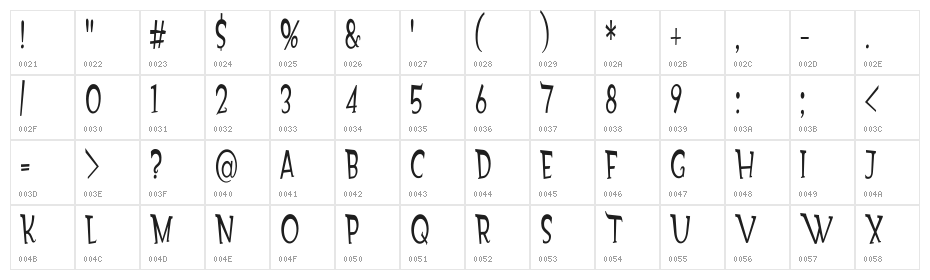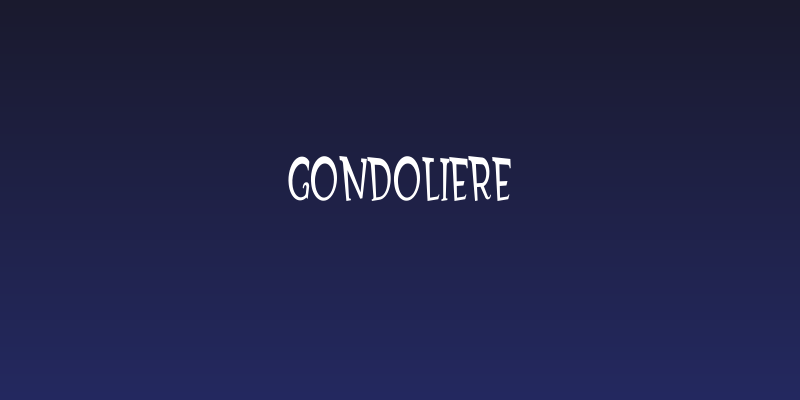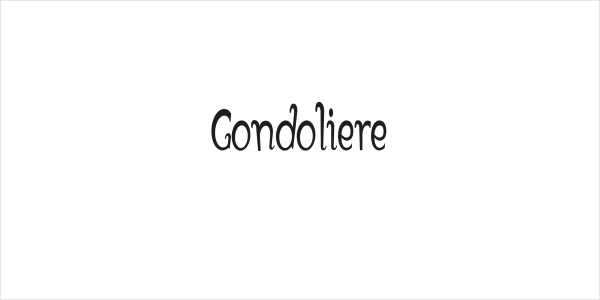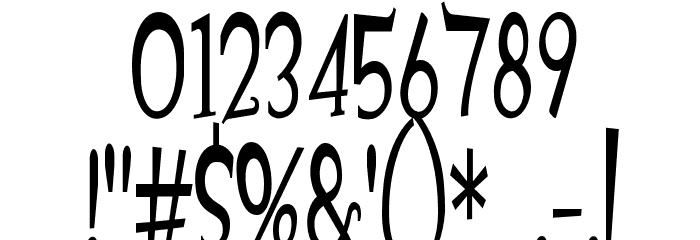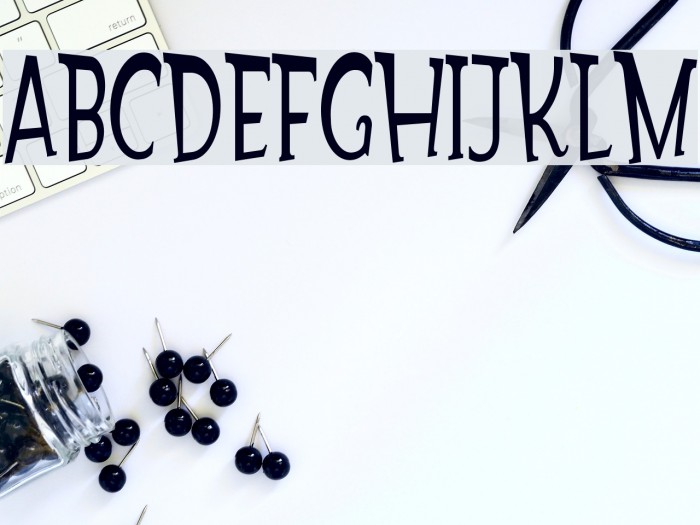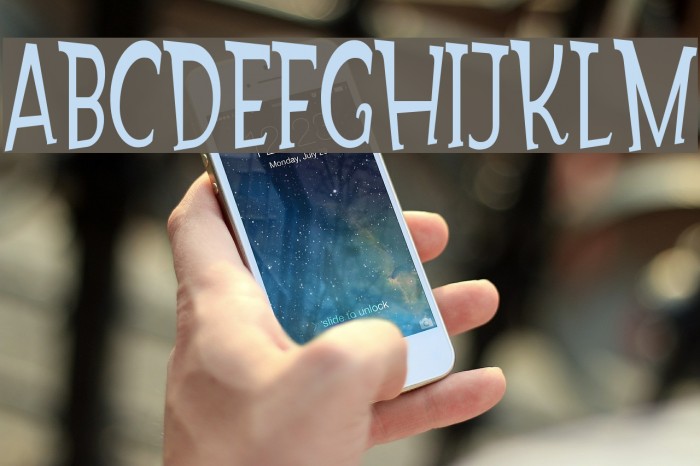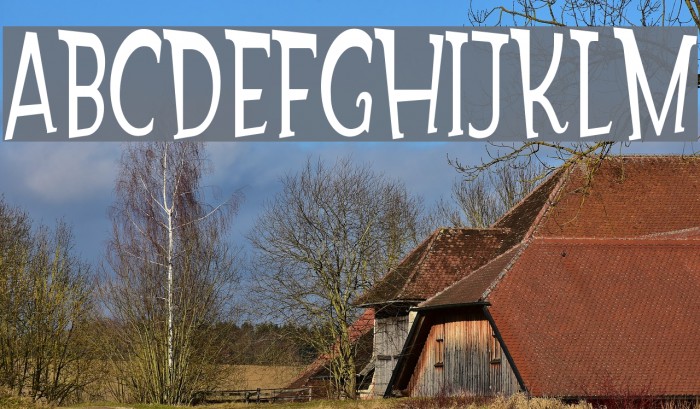
Gondoliere Font
✎ Serif
| Anwendungsfall | Headlines, Logos, Invitations |
| Vorgeschlagene Projekte | Ideal for creative projects such as invitations, greeting cards, posters, and branding materials that require a touch of whimsy and elegance. |